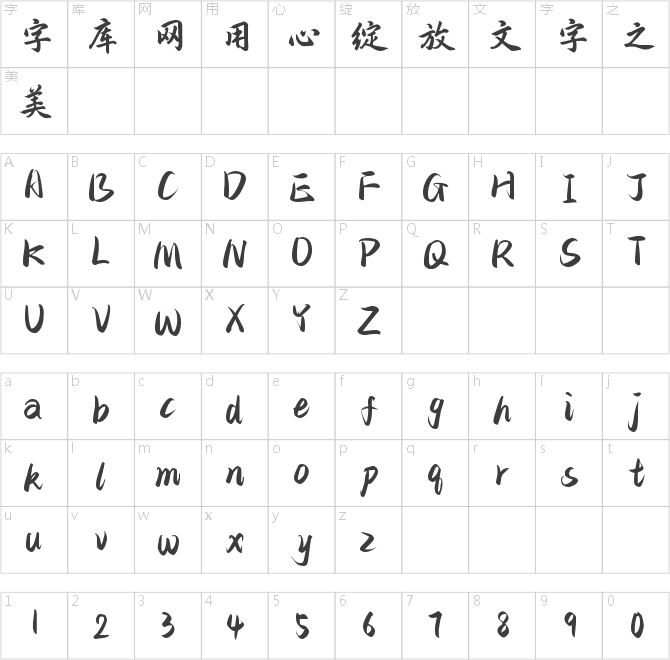
字魂文字博物館聯(lián)名體-銘心楷書 詳情頁
楷書
字魂文字博物館聯(lián)名體-銘心楷書字體字庫是一款讓人賞心悅目、百看不厭的中文字體,適合各類廣告和產(chǎn)品包裝設(shè)計應(yīng)用,字體大小9.16MB,格式為ttf字體,上傳用戶是sygyve520,作者/版權(quán)方為字魂